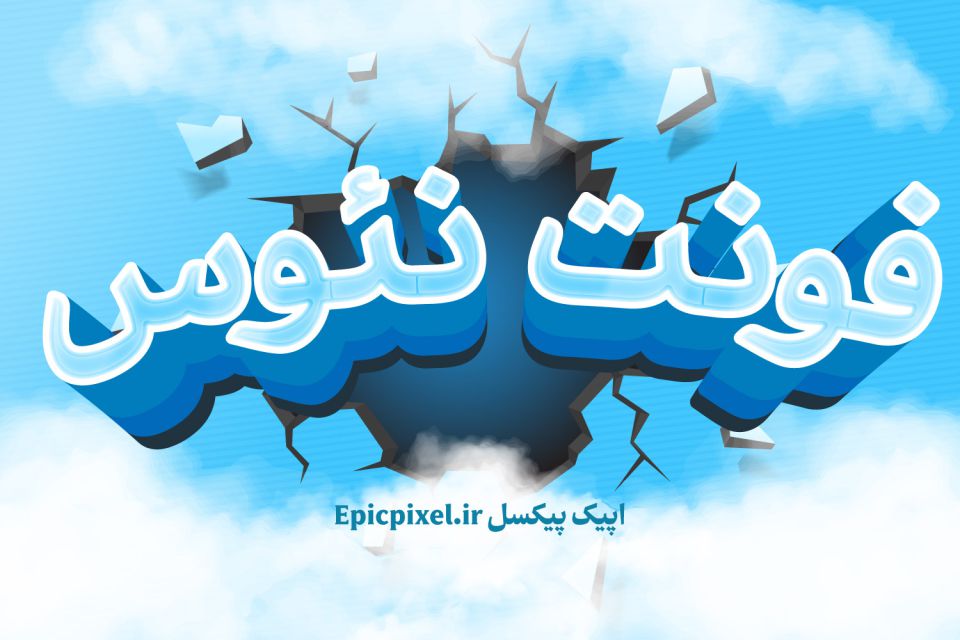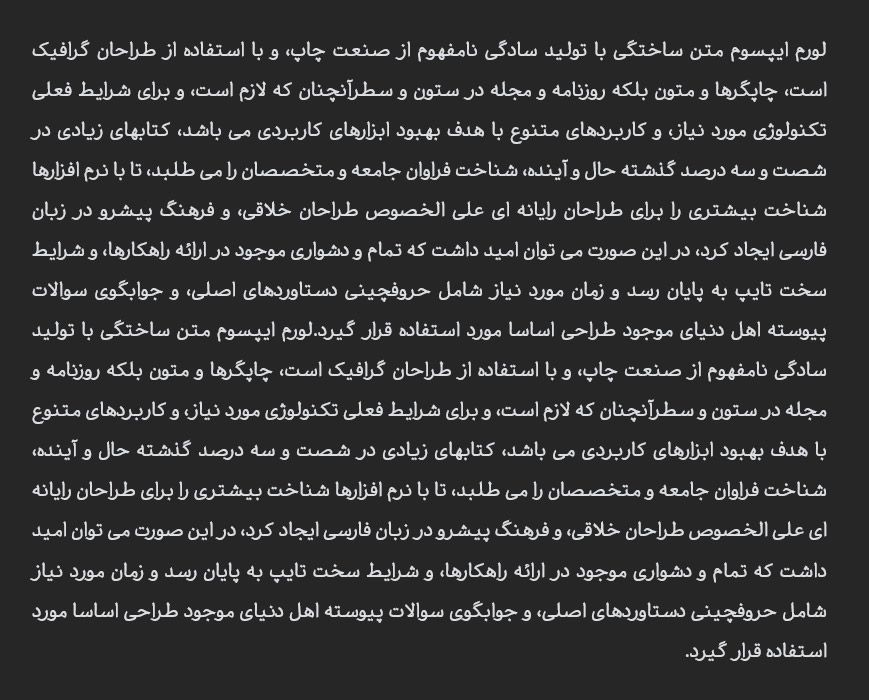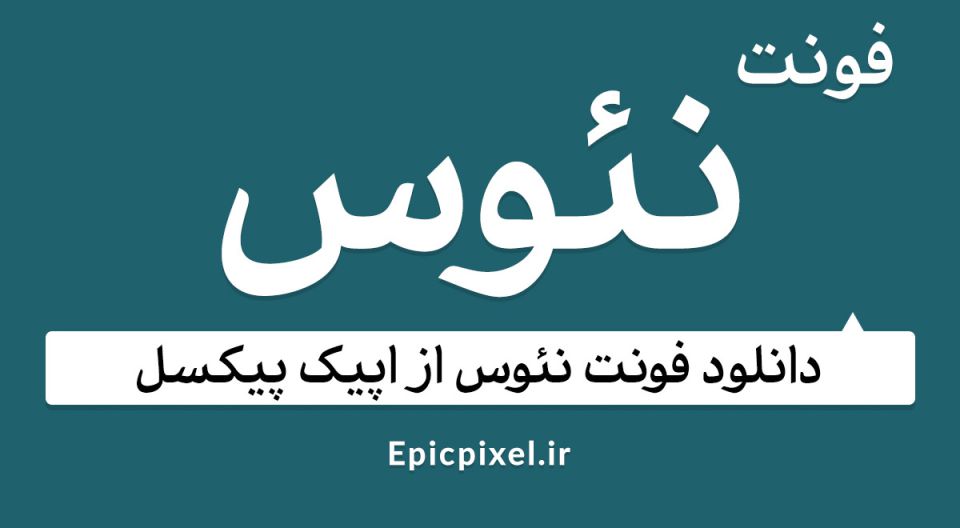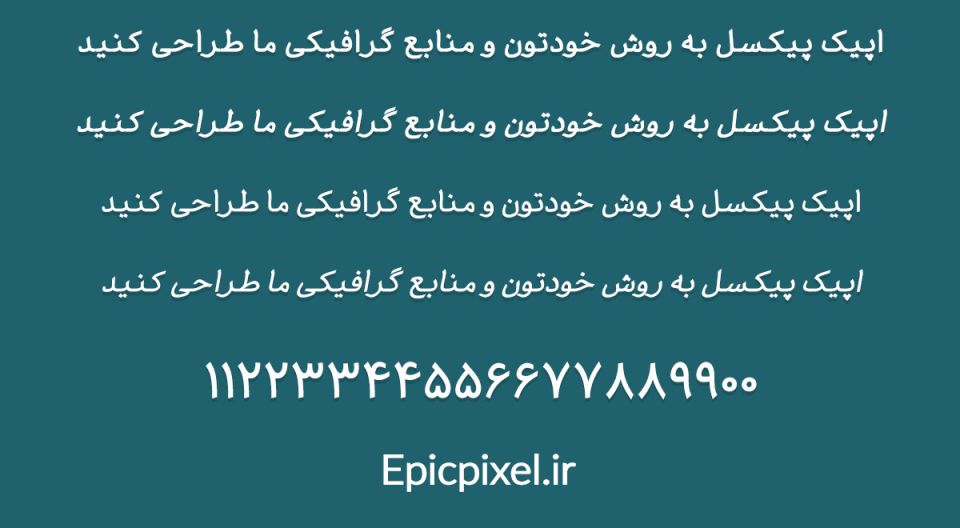
3 فونت نئوس فارسی
چشمهای از زیبایی و خوانایی: دانلود و استفاده از فونت نئوس (Neus) برای پروژههای طراحی شما
جستجو برای فونتهای باکیفیت و خوانا که به پروژههای طراحی شما جلوهای حرفهای ببخشند، امری ضروری است. در میان انبوه فونتهای موجود، فونت نئوس به دلیل سادگی ظاهری، خوانایی بالا و انعطافپذیری فوقالعاده، جایگاه ویژهای پیدا کرده است. این فونت میتواند در طیف وسیعی از پروژهها، از طراحی وبسایت و اپلیکیشن موبایل گرفته تا بروشورها و پوسترها، مورداستفاده قرار گیرد.
در این مقاله جامع، به بررسی کامل فونت نئوس (Neus) و نحوه دانلود و استفاده از آن در پروژههای طراحی خود میپردازیم. با ما همراه باشید!
تاریخچهای مختصر از فونت نیوس
فونت نئوس در سال 2009 طراحی شد. هدف اصلی وی از طراحی این فونت، ایجاد یک فونت هندسی با ظاهری مدرن و خوانایی بالا بود که در اندازههای مختلف به خوبی به نظر برسد. نئوس به سرعت محبوبیت پیدا کرد و به یکی از فونتهای پرکاربرد در طراحی گرافیک تبدیل شد.
| ⭐ توضیحات | دانلود فونت نئوس برای طیف وسیعی از پروژههای طراحی از جمله طراحی وبسایت، اپلیکیشن موبایل، لوگو، برندینگ، بروشور، پوستر و عناوین و تیترها مناسب است. |
ویژگیهای کلیدی فونت نئوس
فونت نئوس دارای مجموعهای از ویژگیهای منحصر به فرد است که آن را به گزینهای ایدهآل برای طراحان تبدیل میکند. برخی از مهمترین این ویژگیها عبارتاند از:
- سادگی ظاهری: نئوس یک فونت هندسی با خطوط ساده و خوانا است. این ویژگی باعث میشود تا در اندازههای مختلف به خوبی نمایش داده شود و برای طیف وسیعی از پروژهها مناسب باشد.
- خوانایی بالا: خوانایی یکی از مهمترین ویژگیهای یک فونت است. نئوس با فاصلهبندی مناسب و فرم ظاهری واضح، خوانایی عالی را حتی در اندازههای کوچک ارائه میدهد.
- انعطافپذیری: نئوس در وزنهای مختلف (Light, Regular, Bold) ارائه میشود که به شما امکان میدهد تا بر اساس نیاز پروژه خود، وزن مناسب را انتخاب کنید.
- سازگاری با زبانهای مختلف: نئوس از الفبای لاتین و همچنین برخی از حروف سیریلیک پشتیبانی میکند. این ویژگی باعث میشود تا برای پروژههای بینالمللی نیز مناسب باشد.
دانلودکاربردهای فونت نئوس در طراحی
به دلیل ویژگیهای ذکر شده، فونت نئوس در طیف وسیعی از پروژههای طراحی کاربرد دارد. برخی از کاربردهای رایج آن عبارتاند از:
- طراحی وبسایت و اپلیکیشن موبایل: خوانایی بالای نئوس، آن را به گزینهای ایدهآل برای متنهای خواندنی در وبسایتها و اپلیکیشنهای موبایل تبدیل کرده است.
- طراحی لوگو و برندینگ: سادگی و خوانایی نئوس، باعث میشود تا برای طراحی لوگو و سایر عناصر مرتبط با برندینگ نیز مناسب باشد.
- بروشورها و پوسترها: خوانایی و انعطافپذیری نئوس، آن را به گزینهای عالی برای طراحی بروشورها، پوسترها و سایر مواد چاپی تبدیل کرده است.
- عناوین و تیترها: با استفاده از وزن Bold فونت نئوس، میتوانید عناوین و تیترهای برجسته و تاثیرگذاری ایجاد کنید.
نکاتی برای استفاده از فونت نئوس
- از نئوس در کنار فونتهای دیگر: نئوس را میتوانید به تنهایی یا در کنار فونتهای دیگر استفاده کنید. برای مثال، میتوانید از نئوس برای عناوین و از یک فونت Serif برای متنهای اصلی استفاده کنید.
4. چه فونتهایی با نئوس سازگاری دارند؟
نئوس با طیف وسیعی از فونتها سازگاری دارد. برای مثال، میتوانید از نئوس برای عناوین و از یک فونت Serif برای متنهای اصلی استفاده کنید.
5. بهترین کاربردهای فونت نئوس کدامند؟
نئوس برای طیف وسیعی از پروژههای طراحی از جمله طراحی وبسایت، اپلیکیشن موبایل، لوگو، برندینگ، بروشور، پوستر و عناوین و تیترها مناسب است.